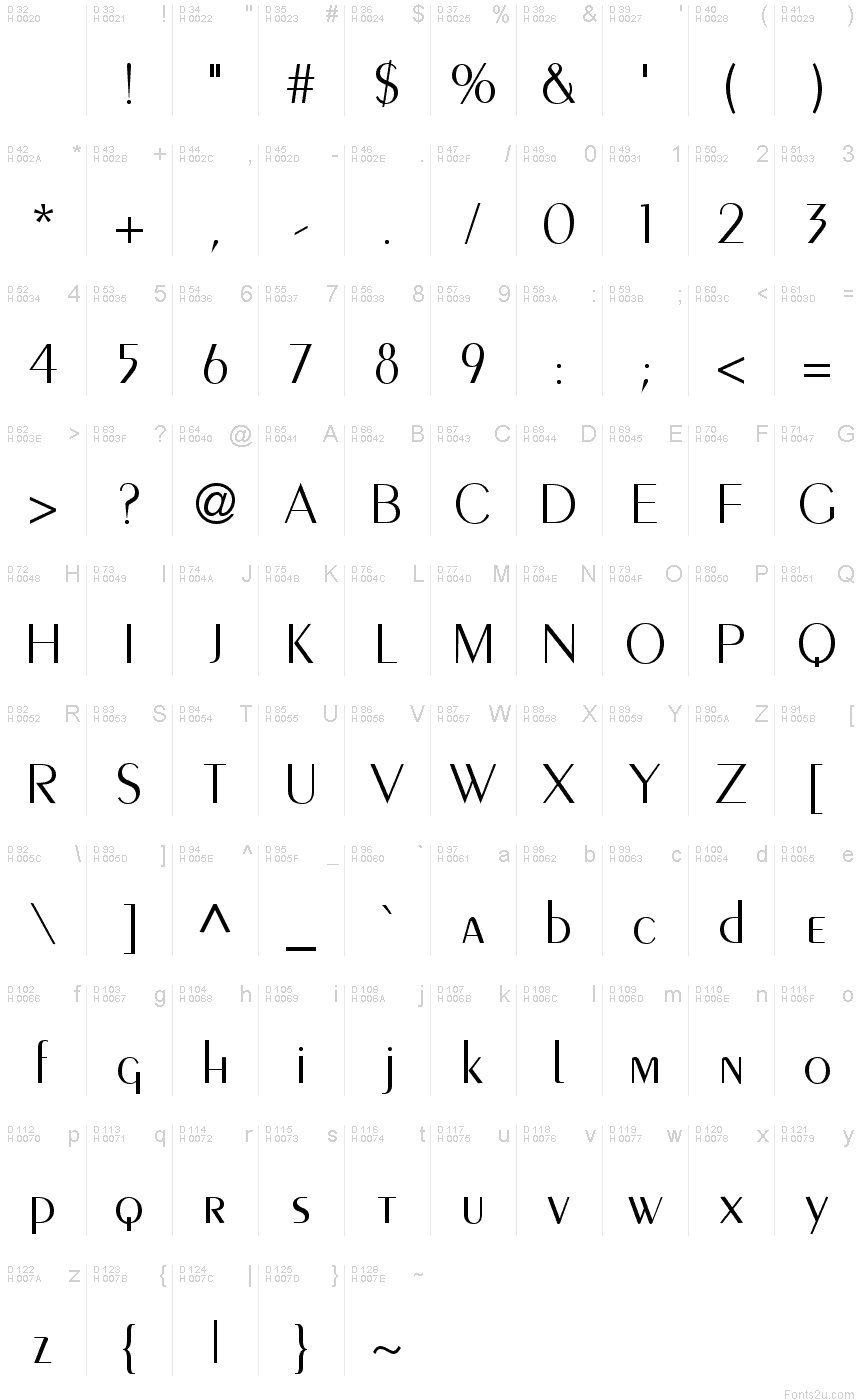
Peridot Regular
Peridot to darmowy, humanistyczny bezszeryfowy krój pisma od Rubicon Computer Labs, wydany w 1997 roku, wyróżniający się spokojną, lekko kaligraficzną elegancją. Litery łączą w sobie czyste, oszczędne formy z wyraźnym kontrastem kresek i zaokrąglonymi krzywiznami, dzięki czemu font sprawia wrażenie bardziej literackiego niż geometrycznego i unika zbyt „biurowego” charakteru.
Dzięki temu naturalnie pasuje do okładek książek, brandingu artystycznego, nagłówków w magazynach, opakowań butikowych czy napisów filmowych — wszędzie tam, gdzie darmowy font ma dodać projektowi wdzięku, nie stając się przy tym przesadnie ozdobnym. Sprawdza się również w krótkich nagłówkach i monogramach, ponieważ wysokie, proporcjonalne kształty i miękkie łuki nadają nawet kilku literom przemyślaną, redakcyjną prezencję.